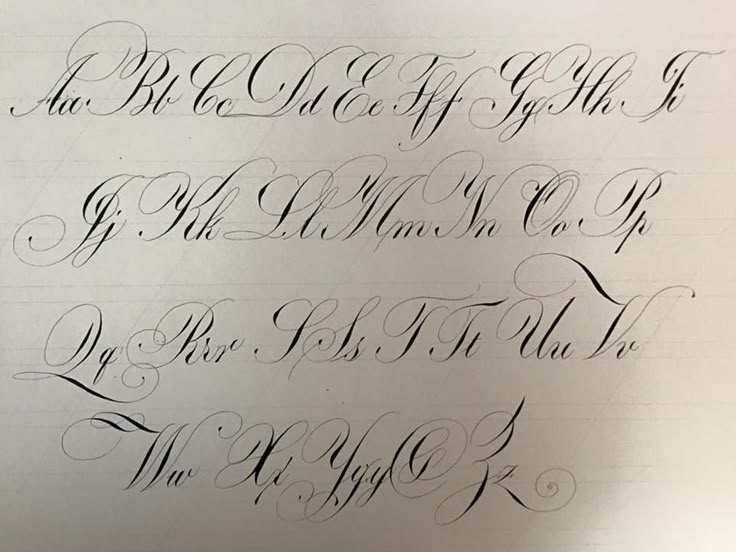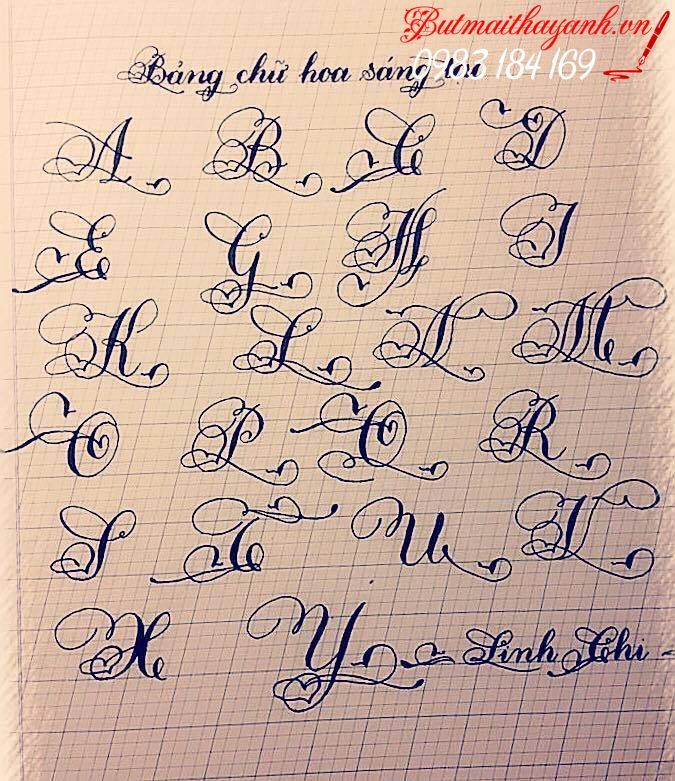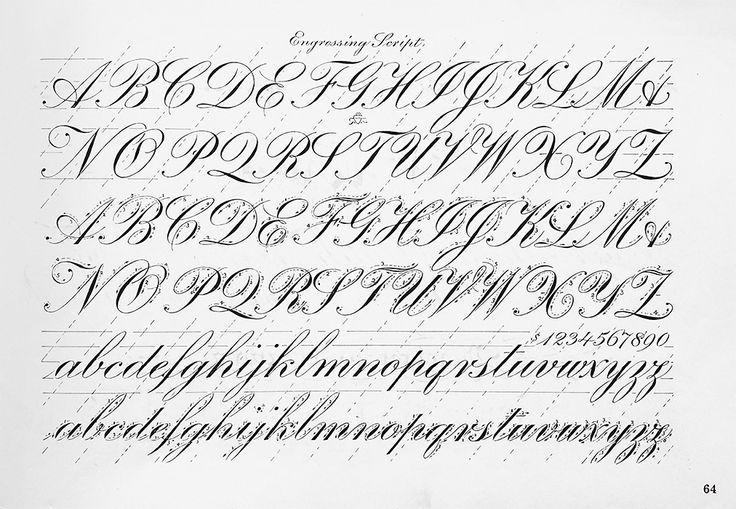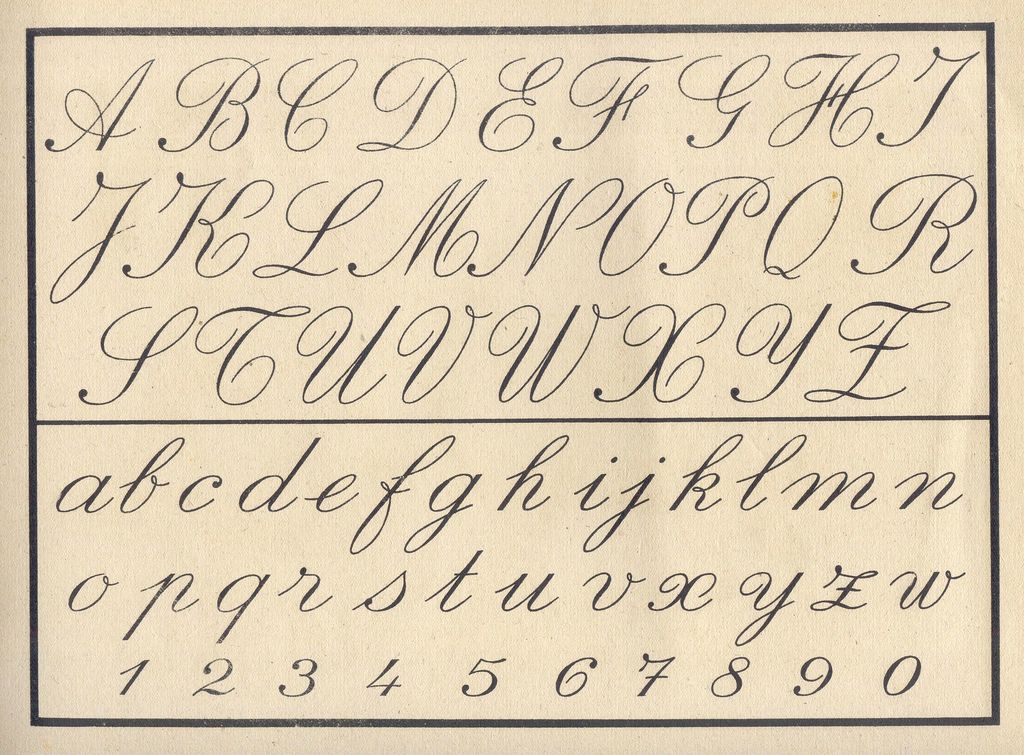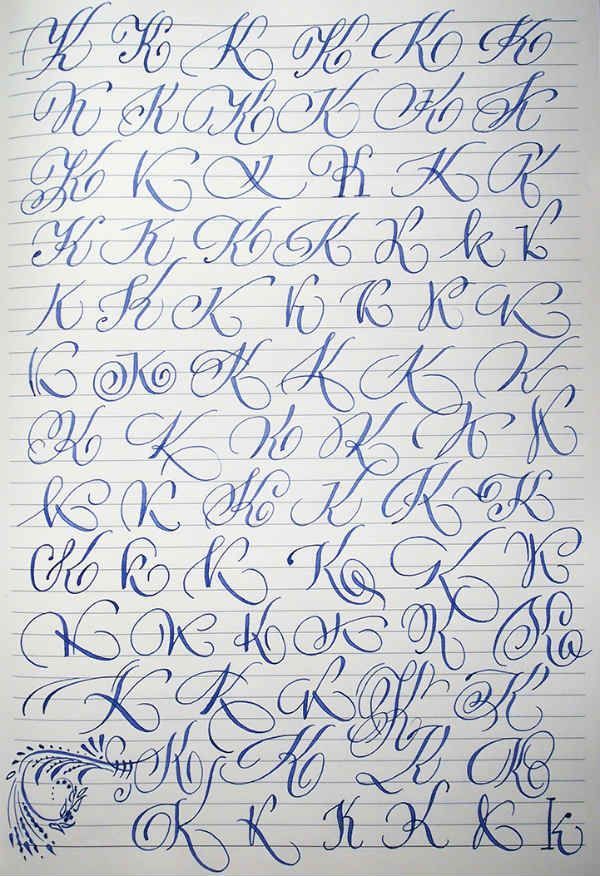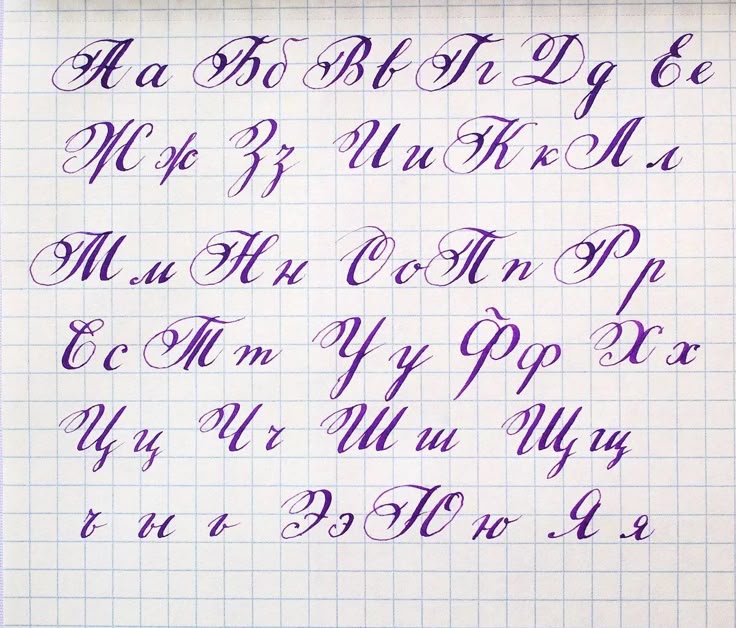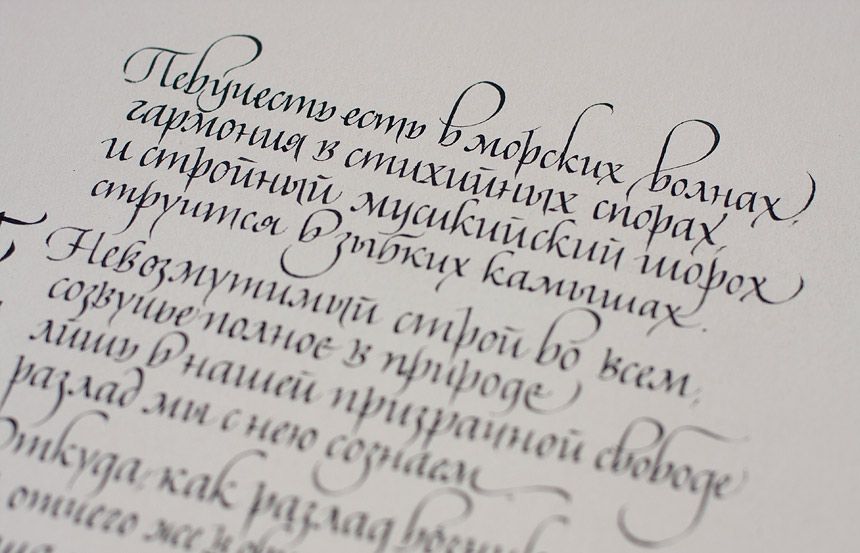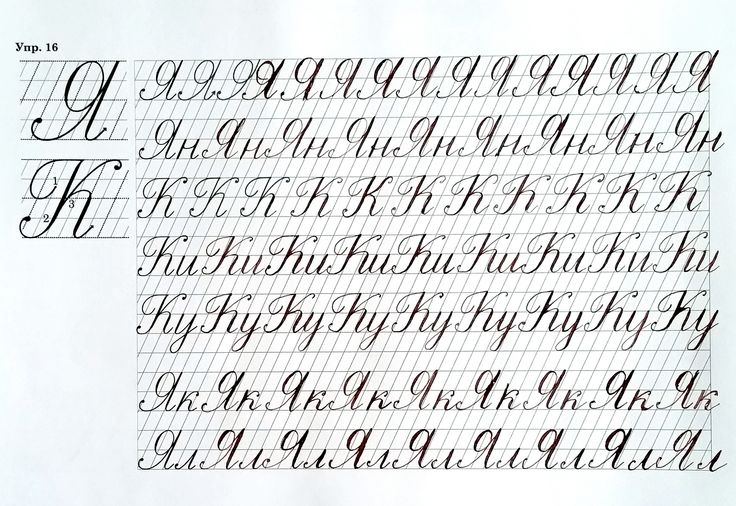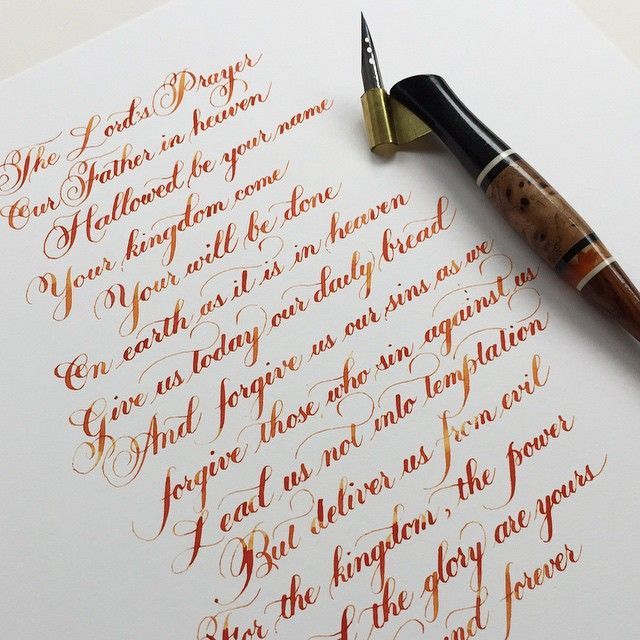
Каллиграфия — таблетка от дурного настроения
Зачем православным каллиграфия? Для работы? Для учёбы? Для молитвы? «От нервов» и для здоровья? На все эти вопросы можно ответить утвердительно. В чудодейственных свойствах занятий каллиграфией Мария Строганова из редакции сайта «Правмир» убедилась на курсах при Пятницком подворье Троице-Сергиевой лавры в Сергиевом Посаде. Вдохновитель и создатель курсов — протоиерей Павел Великанов, настоятель Пятницкого подворья, преподаватель — Виктор Новиков, художник-график, член Союза художников, иконописец.
Сегодня не учебный день, и всё равно в класс каллиграфии в цокольном этаже Введенского храма заглядывают прихожане — каллиграфия требует постоянства. Преподаватель Виктор Новиков раскладывает учебный материал и рассказывает, что освоить навыки правильного и красивого письма может каждый.
Для первых шагов в каллиграфии не нужно иметь красивый почерк или художественный талант — важна усидчивость и практика.
— В детстве у меня был довольно плохой почерк, но я любил имитировать почерки других. Смотрю на свои школьные тетради — одна страница написана одним почерком, вторая — другим.
— Со справками о болезни от родителей проблем не было?
— Вот именно. Кстати, каллиграфия — это не только красиво, но и полезно. Некоторые врачи считают, что нет таких болезней, которые не излечиваются каллиграфией. Сам я эксперименты не ставил, но говорят, что так. Когда мы пишем, то берём перо тремя пальцами, и получается, что задействуются определённые зоны мозга. Я читал, что в полной мере каллиграфию может заменить только скрипка. Но чтобы быть скрипачом, нужен и слух, и умение, а тут просто пишешь буковки — и пожалуйста: мозг работает почти на сто процентов.
— А письма простой ручкой это не касается?
— Нет. Когда мы пишем шариковой ручкой — это непрерывное письмо: мы ставим ручку, как нас в школе учили, и пишем, не прерываясь.
В каллиграфии мы задумываемся над каждой буквой, над каждым движением. Это, конечно, медленнее, но пользы гораздо больше.
Шариковая ручка очень испортила и людей, и культуру. Вот китайцы и японцы не отказались от своих иероглифов, которые пишутся кисточкой. У нас есть неполная замена перу — перьевая ручка. Но когда пишешь пером, ты просто вынужден писать правильно, поворачивая лист, руку или саму поверхность так, как нужно для буквы.
— Какая ещё может быть польза от занятий каллиграфией?
— Конечно, мы пишем не только ради удовольствия или ради красоты буквы. Важно, что мы думаем над тем, что именно пишем. Вот, например, когда на занятиях мы переписываем Священное Писание, представляете, сколько раз человек прокрутит в голове каждую фразу, насколько текст отложится у него в памяти? А сейчас часто пробежал глазами в интернете — и всё.
Раньше для монахов было нормальной практикой переписывать Священное Писание. И Иоанн Лествичник, и Фёдор Студит говорили: пусть в монастырях будет каллиграфия.
Во-первых, чтобы распространять книгу, а во-вторых, для изучения Священного Писания и молитвы. Как в школе говорили: переписал бы раз учебник по физике — знал бы физику.
Виктор Новиков
Если родители привели ребёнка на занятия каллиграфией с целью улучшить его почерк, чуда не произойдёт. Зато письмо пером может воспитать усидчивость. Для детей у Виктора есть специальные плакатные перья, а вместо букв — разные животные. Их, как и буквы, надо писать за несколько движений пером, а не рисовать:
— Если ребёнок захочет нарисовать такую красивую птицу, — показывает Виктор, — он долго будет мучить это карандашиком, а так раз — и получилось. Для детей очень интересно, и заодно они учатся чисто писать. У меня был на занятиях один очень резвый ребёнок, он за урок три раза разлил тушь — самому неприятно, поэтому в дальнейшем он стал осторожнее, внимательнее. Раньше дети хотя бы перьевыми ручками писали, старались, а теперь и клякс не бывает — пиши как хочешь.
— Прописи в школе не направлены на то же, что и каллиграфия?
— Если бы прописи писали тонким пером, ввели урок чистописания, была бы польза.
А сейчас непонятно что — ни шрифтом не занимаются, ни над почерком не работают. Каллиграфия ведь и появилась как красивописание. И чем красивее, тем лучше, потому что чем буква красивее, тем она внятнее, приятнее глазу.
Прежде всего, говоря о каллиграфии, важно понимать, что мы не рисуем, а пишем буквы. Каллиграфия — это рукописный шрифт. С появлением книгопечатания каллиграфия как вид искусства забылась, появились печатные книги, а писать практически перестали. Только в начале ХХ века каллиграфия стала возрождаться. И интересно, что когда стали смотреть на древние книги, людям казалось, что все буквы в них нарисованы, даже в голову не приходило, что каждая буква пишется за два-три движения. Тогда Эдвард Джонстон, английский каллиграф, взял ширококонечное перо и написал те же самые буквы. Вот с его именем и связано возрождение современной каллиграфии.
Виктор раздаёт бумагу, перья, ставит на стол баночки с тушью. Для урока каллиграфии нужно иметь:
• чертёжную бумагу;
• чёрную тушь в баночке;